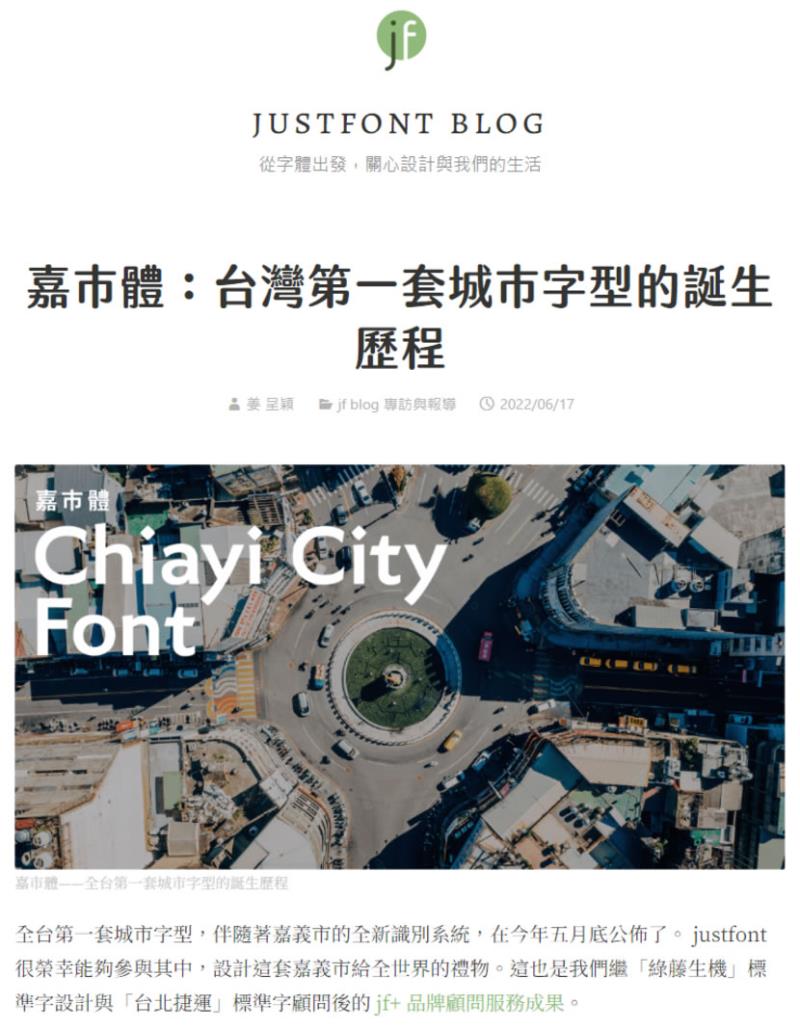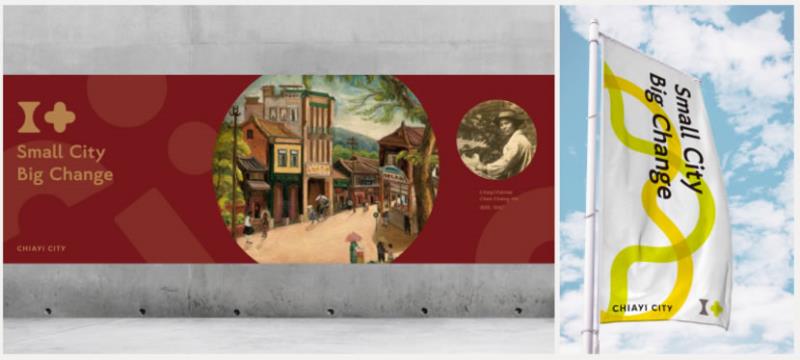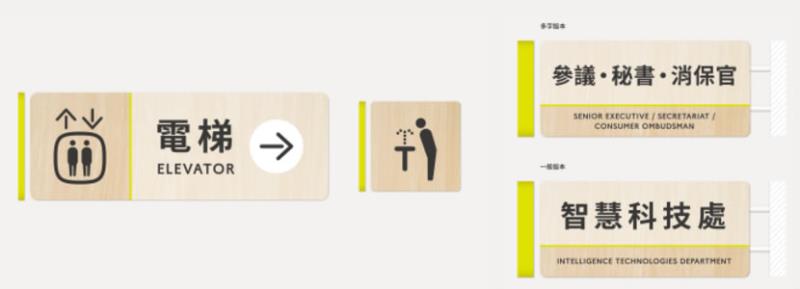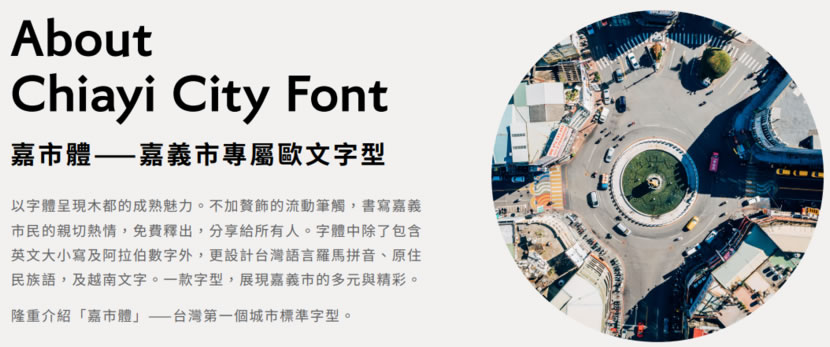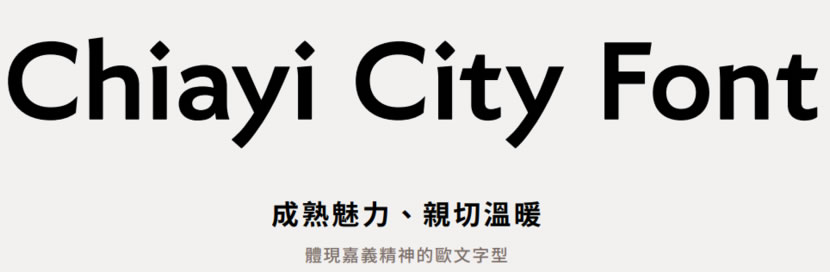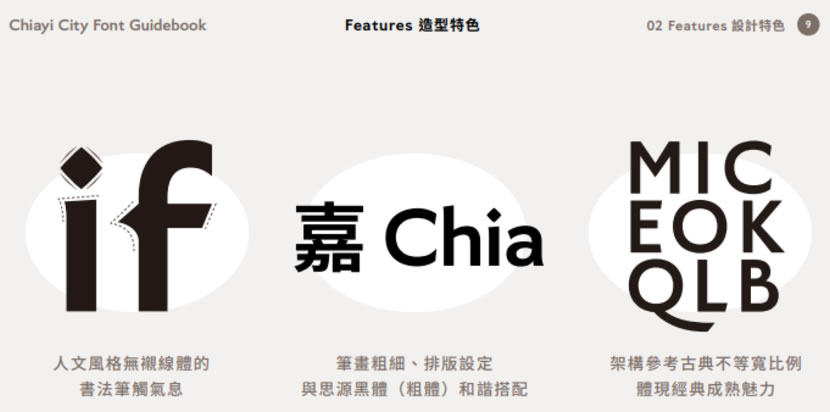
「嘉市體」是由嘉義市政府出資所設計製作的城市標準字型,也是臺灣第一個城市標準字型。它的字體架構取材經典字體比例,映射嘉義市的成熟魅力,並取法歐文書法家 Edward Johnston,字體流動的筆觸使人有親切溫暖的感受,代表嘉義市民的親切熱情。嘉市體除了中文、英文大小寫及阿拉伯數字外,更設計臺灣語言羅馬拼音、原住民族語及越南文字,期由字型展現嘉義市的多元與精彩。
嘉市體字型不但免費且還是可以商業使用的字體,任何人都可以從嘉義市政府網站下載使用。目前,嘉市體已經在市政府內指示牌、公共場所指標、網站等處,持續推廣。嘉義市政府希望透過這款字體,把嘉義的特色和魅力推廣至國際,增加對嘉義的認同感和吸引力。